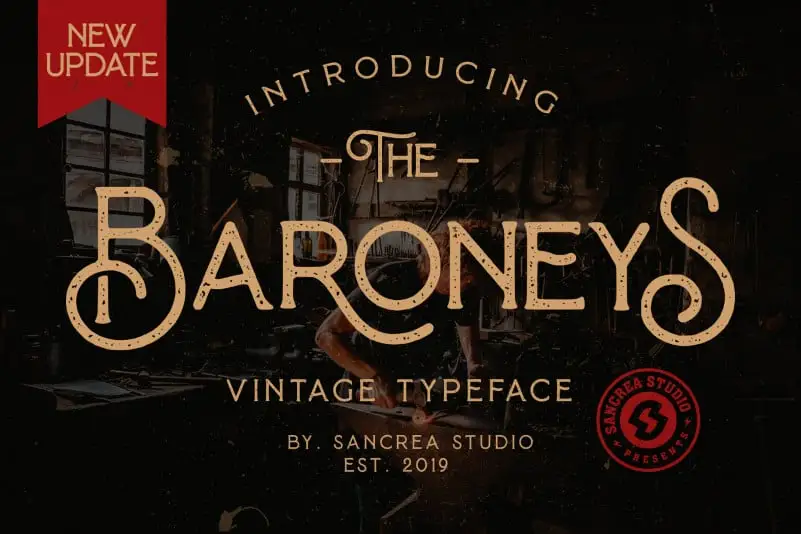
Baroneys – Vintage Typeface – Download Grátis
Olha aqui uma fonte vintage serif chamada Baroneys que você vai adorar para seus próximos projetos criativos. Desenvolvida pelo designer Ade Santani, da Sancrea Studio, essa fonte vintage traz um toque de nostalgia e elegância ideal para trabalhos como arte, cartões modernos, design de livros, panfletos ou até mesmo design de objetos decorativos e emblemas de marca. Suas linhas finas e elegantes são perfeitas para uma aposta vintage que vai marcar sua identidade no meio da comunicação visual. Não importa o tipo de projeto que você está planejando, essa fonte tem um lugar especial. Seja para destacar seu design em letras modernas ou para dar um toque sofisticado aos seus trabalhos de arte pop vintage, Baroneys é uma escolha confiável e criativa.